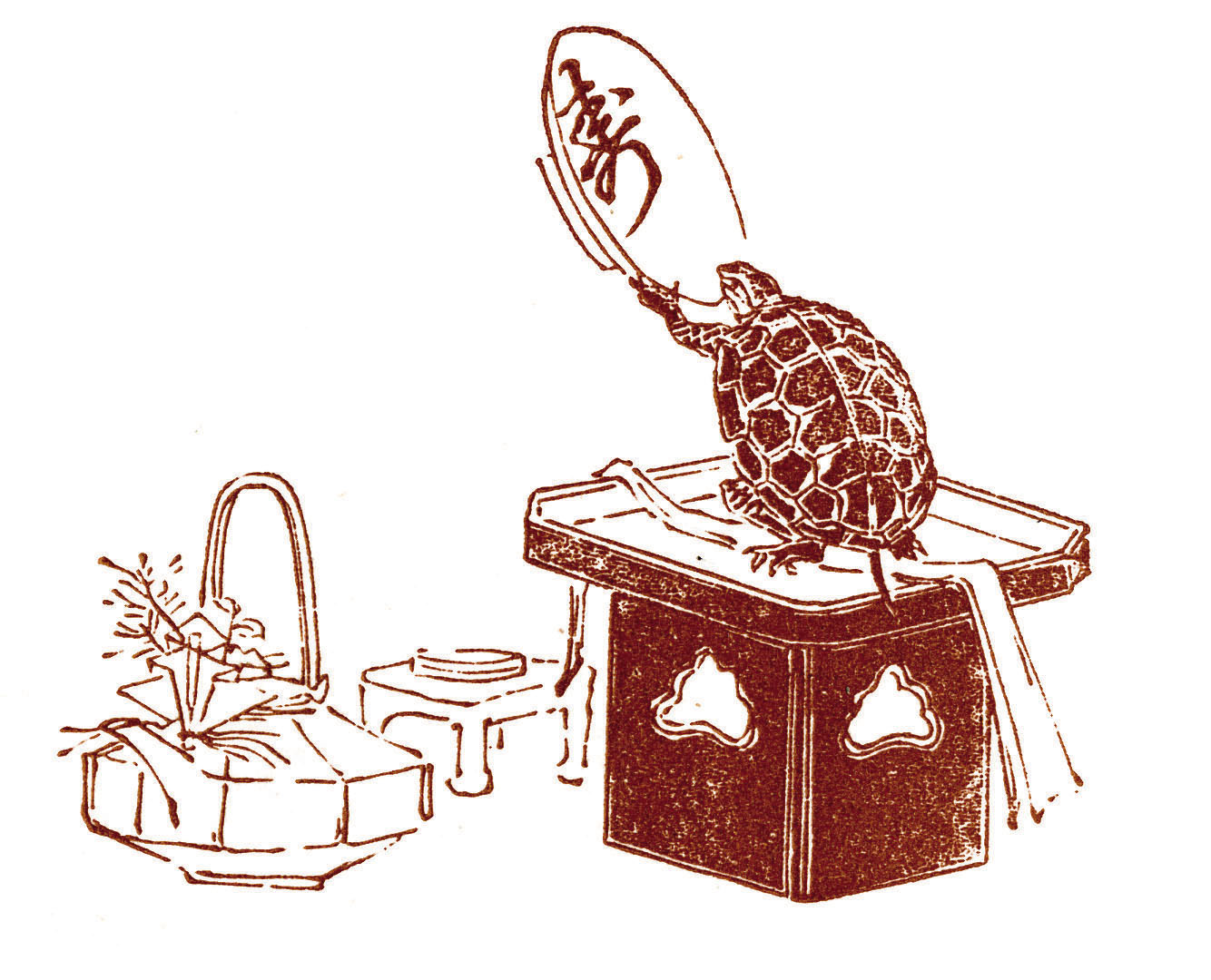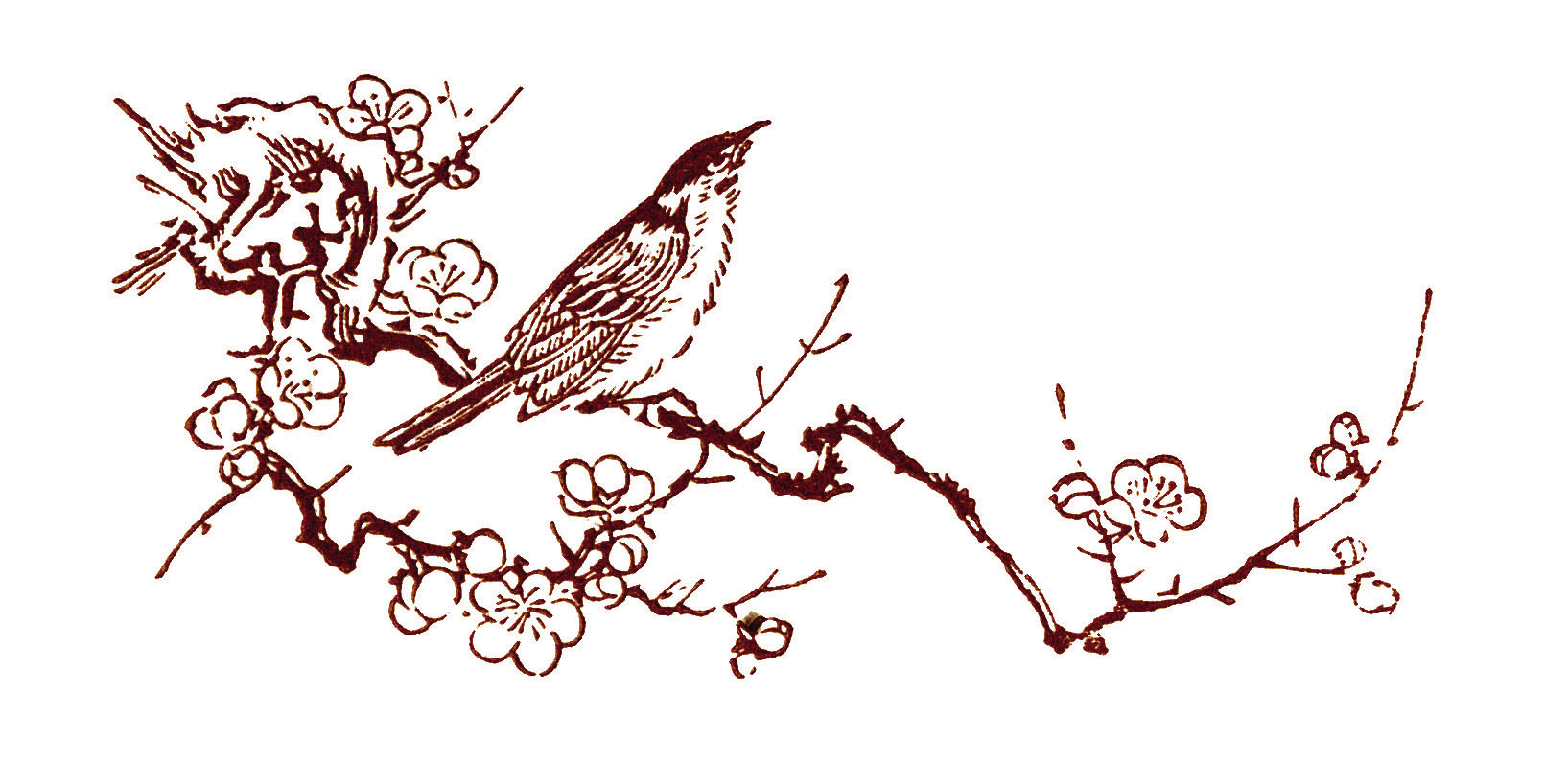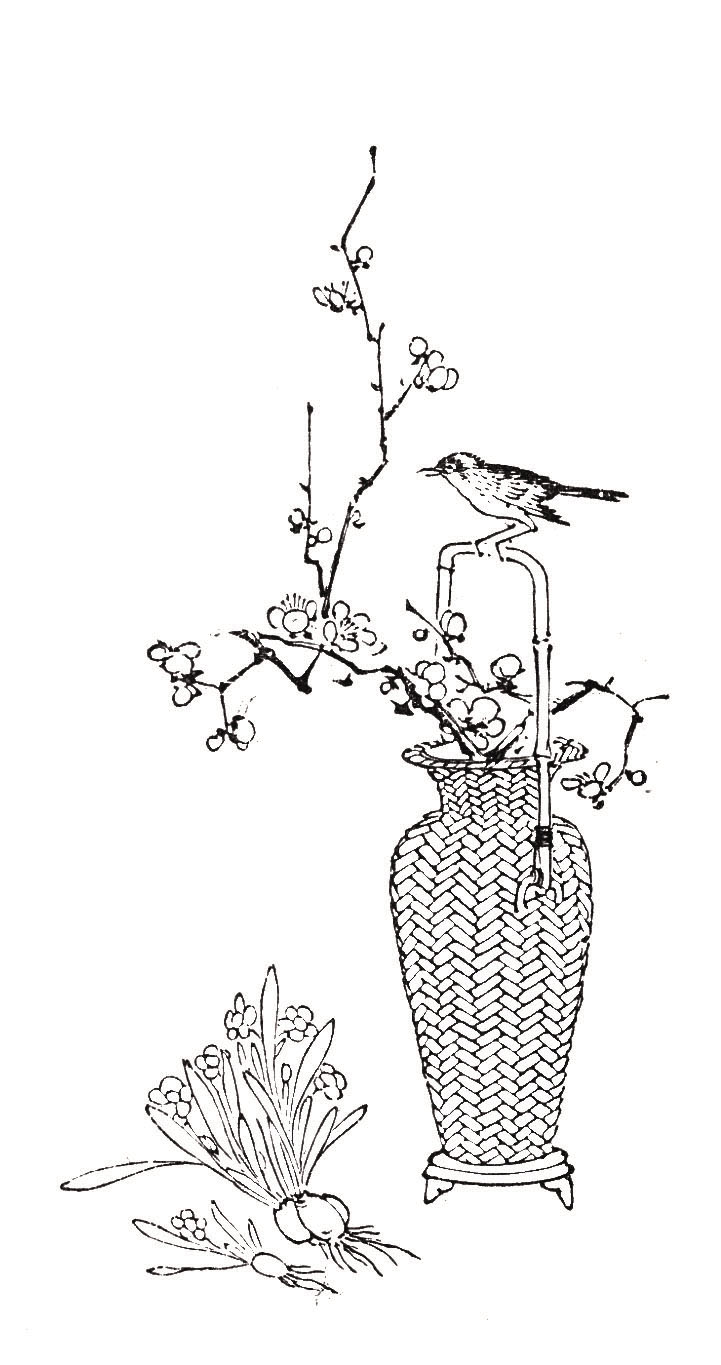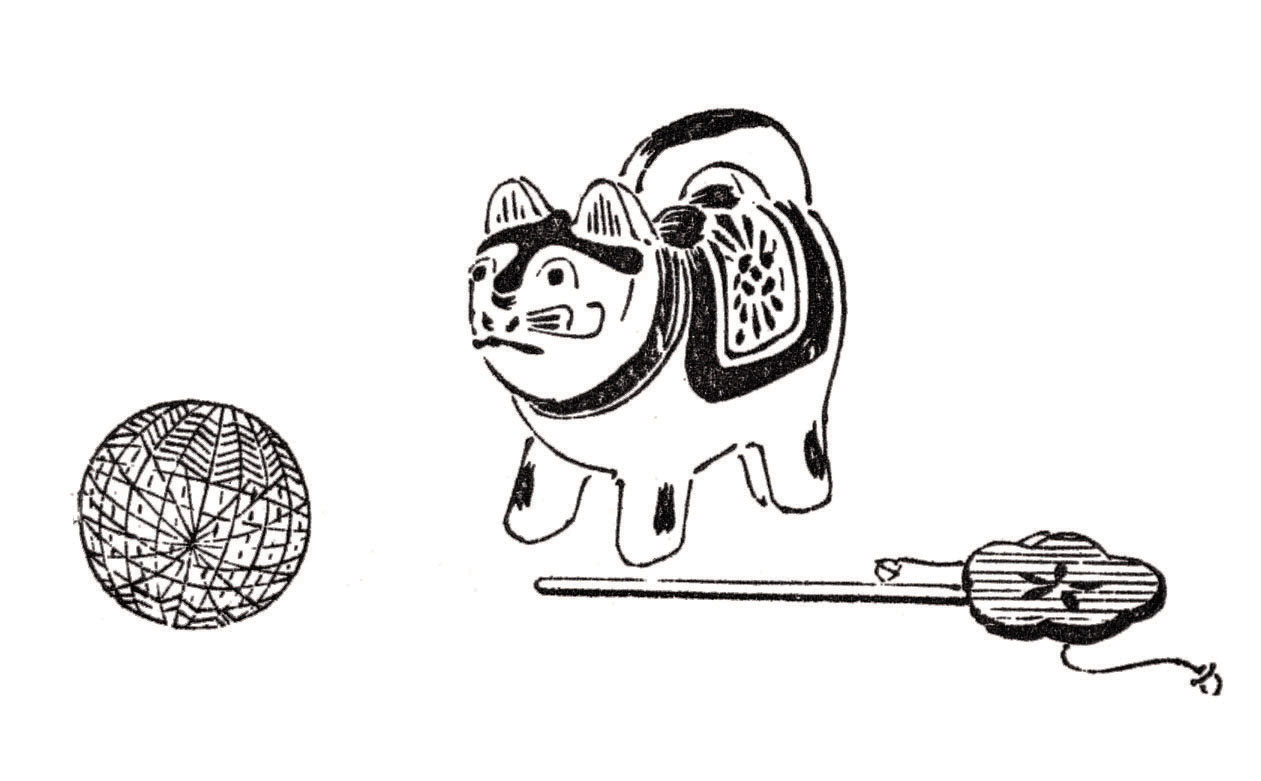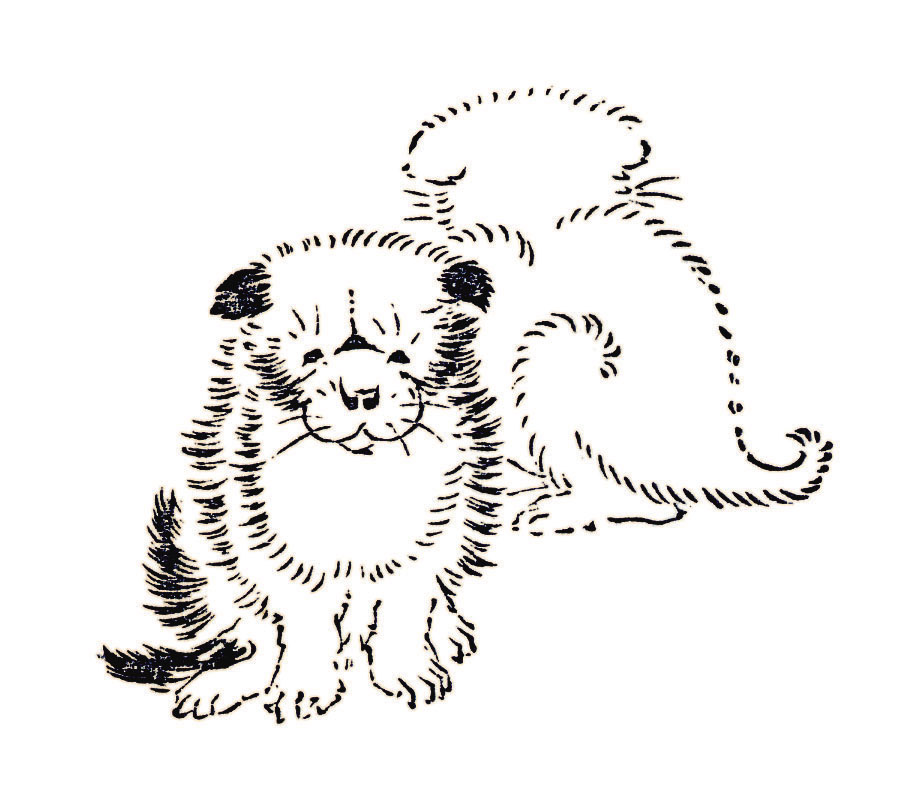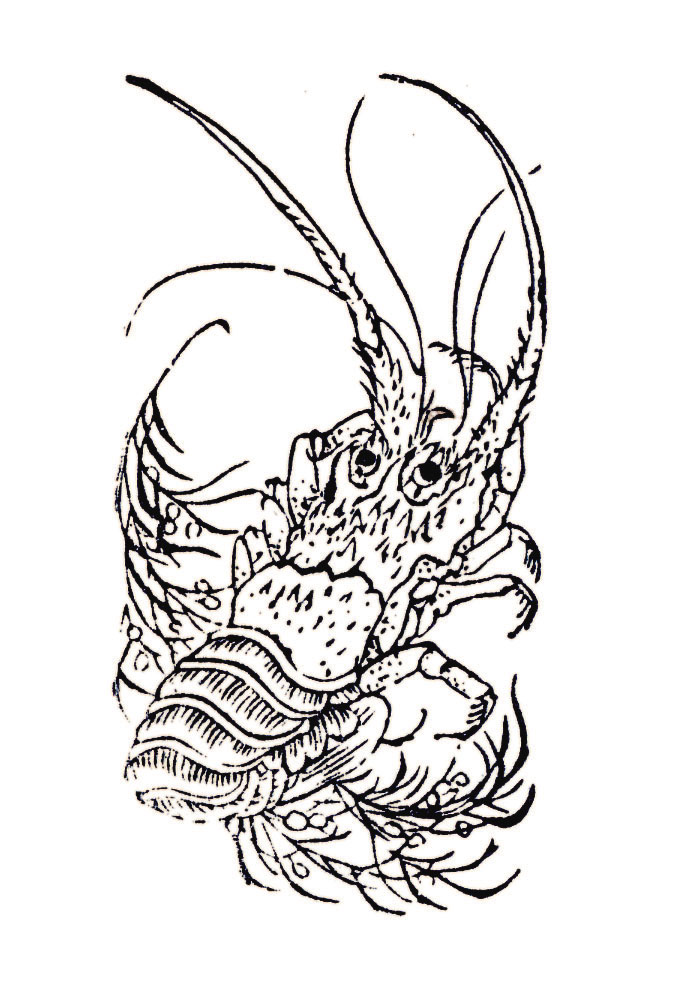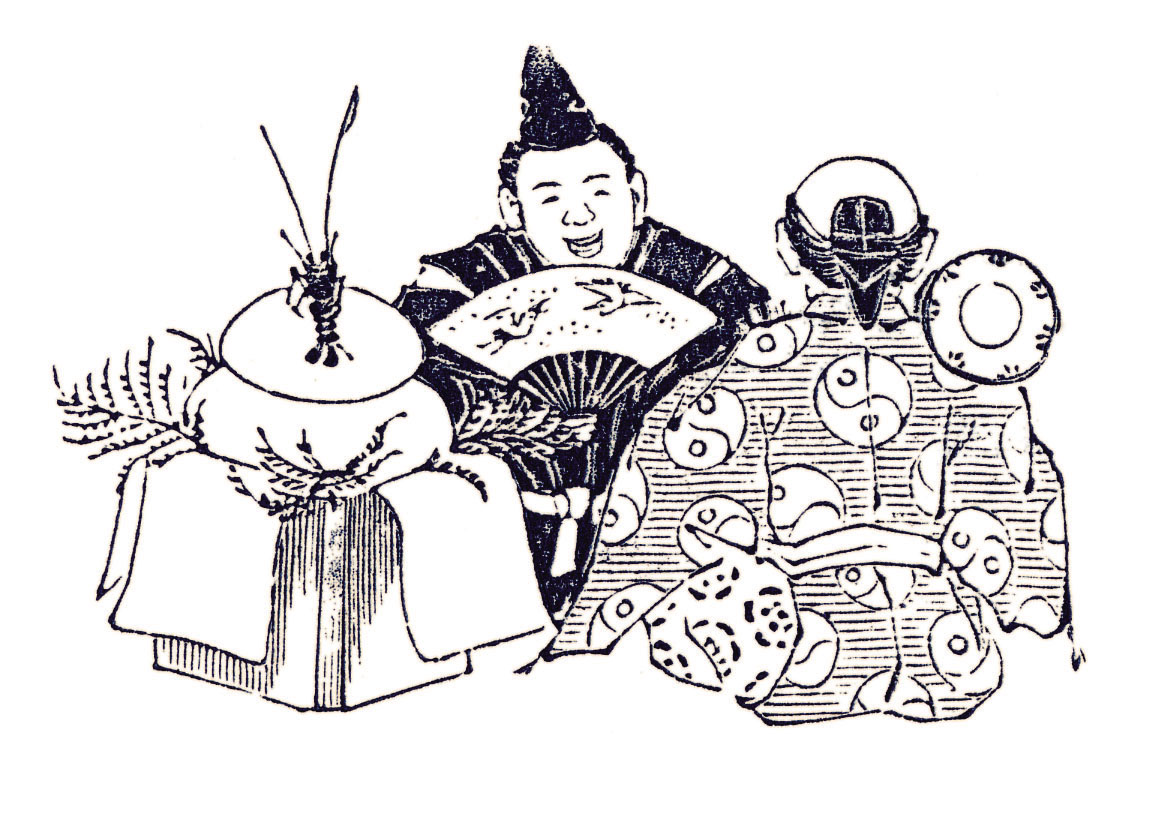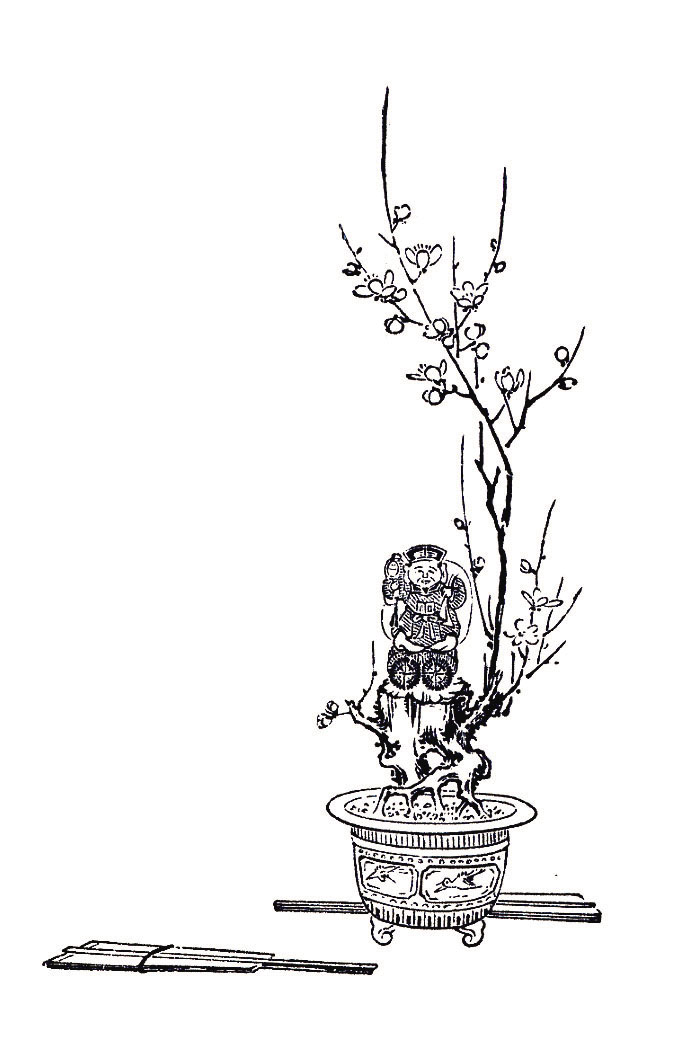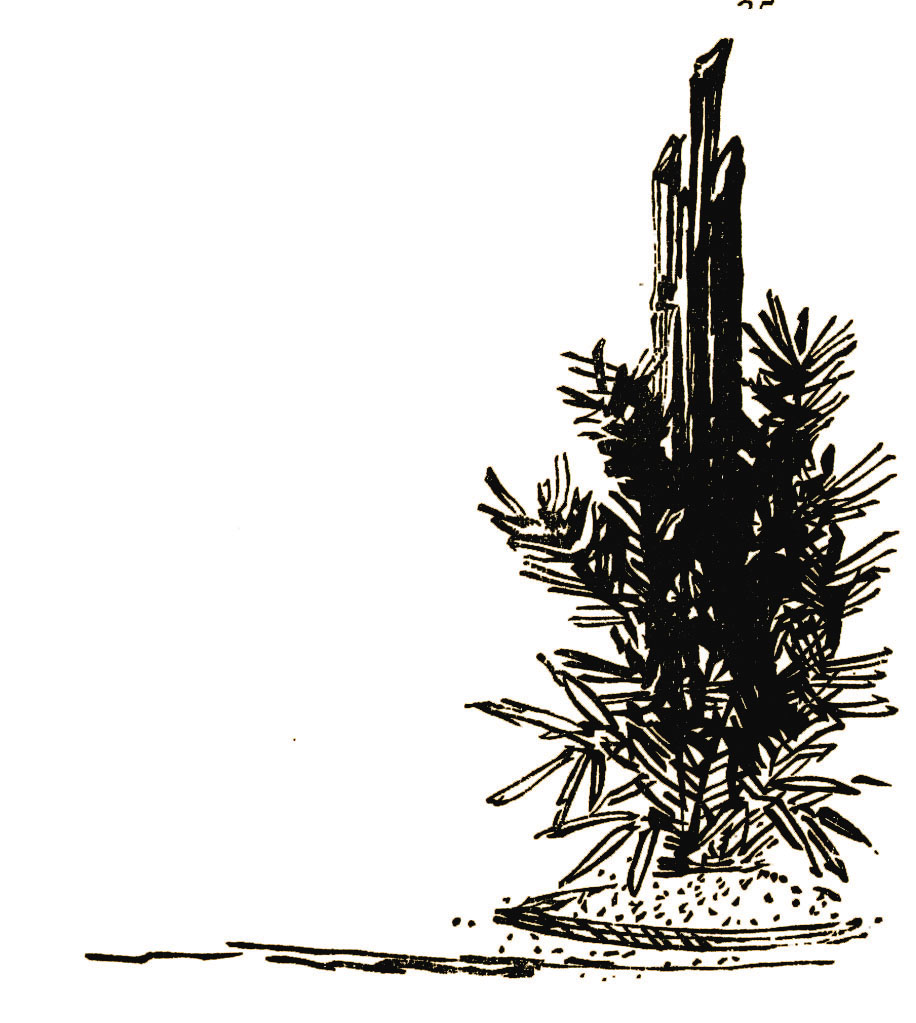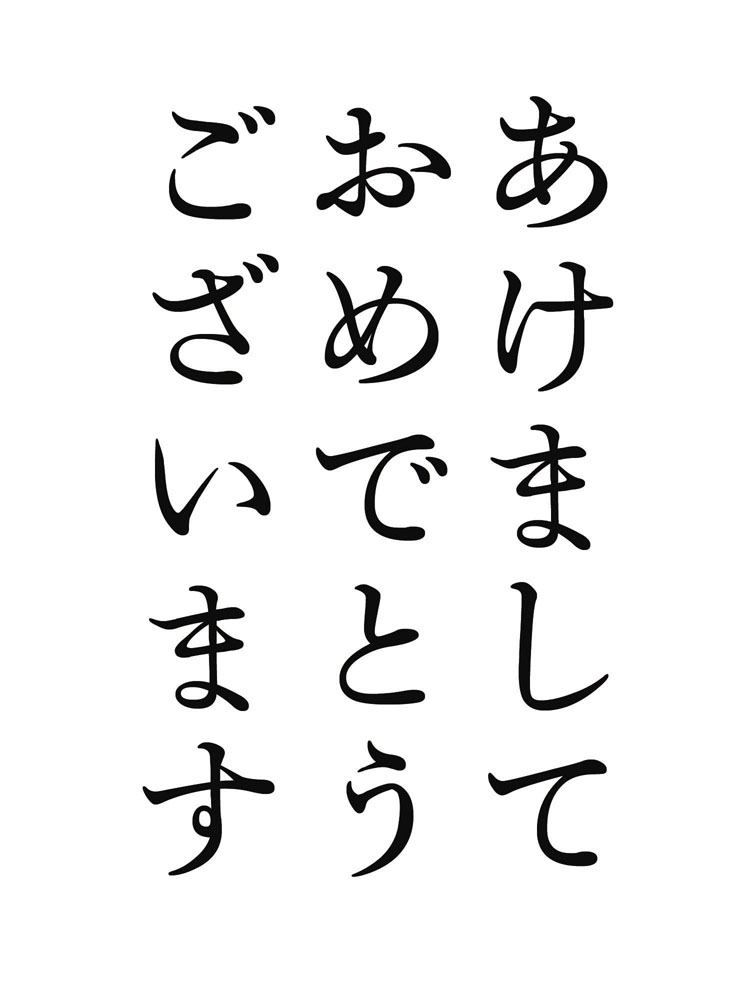
秀英体のコネタ
第14回 大正3年『活版見本帖 Type Specimens』から年賀状を作ろう!
今年も寒さが厳しくなってきました。年の瀬です。
そして年末年始といえば、年賀状を作る季節です。手紙をやりとりする機会のめっきり減った昨今、それでもやはり年賀状は気持ちをこめて、お世話になった方や遠くに住む方に送りたいものですよね。便利な年賀状作成ソフトを使ってパソコンで年賀状を作る方も多いと思います。そこで今回の秀英体のコネタは、一年間のご愛顧に感謝いたしまして、秀英舎・大日本印刷が誇る最大規模の見本帳、大正3年版『活版見本帖 Type Specimens』から、来年の干支である犬やその他お正月らしいおめでたい絵柄をピックアップ、みなさまの年賀状にぜひご利用ください。
2006の干支、ワンコ集合
張り子の犬。そばにあるのは鞠と梅の花をかたどったデンデン太鼓です。
むくむくの仔犬。最近街中にいるのはお洒落な犬ばかりで、こういう犬を見かけませんね……。
扇子をくわえた仔犬。ぽちゃぽちゃしてておなかが地面につきそうです。しっぽがかわいすぎます。
りりしい犬。この犬は最近描かれたようなおしゃれぶりです。上の犬とはずいぶん違います。
ちょうちょと犬。短くカールしているしっぽにもご注目。
仔犬たちがじゃれあっている様子ですが、じっと見ているとだんだん猫のようにも見えます……
お正月らしいおめでたい絵柄
亀とお屠蘇。お屠蘇を飲むときは、東を向いて飲むそうです。
梅に鶯。新春らしい絵柄といえばこれですよね。
梅に鶯 その2。足元にあるのは水仙でしょうか。新春に咲くこの花は、中国では縁起物として欠かせません。
伊勢海老。松葉のうえで跳ねています。長いひげが長寿を連想させるとして縁起のいい食べ物です。
鏡餅。真中の人が広げる扇には下向きに飛ぶ鶴が描かれており、これはしあわせが降りてくるという縁起柄です。
日の出。岩のバランスから、三重にある二見夫婦岩の絵だと思われます。
大黒さま。梅の盆栽のうえに、豊作の神様・大黒天が座っています。扇は末広がりで縁起のいい柄です。
門松。門松が出るとお正月という感じがしますよね。29日と31日を避けて飾ります。
松の枝。雪の中でも緑をたたえるため、縁起のいい植物の代表です。
鶴。いわずと知れた長寿のシンボルです。
「あけましておめでとうございます」を秀英体で
そして! お正月のご挨拶を秀英体で組んでみてはいかがでしょうか。秀英初号・秀英四号・秀英細明朝体の3書体の画像をご用意しました。
若干太いかな、と思われるかもしれません。現在研究中のディスプレイ表示用書体を使っているためです。細い線がかすれにくくなっていますのでプリントゴッコなどの利用にもいかがでしょうか。
秀英4号
秀英初号
秀英細明朝